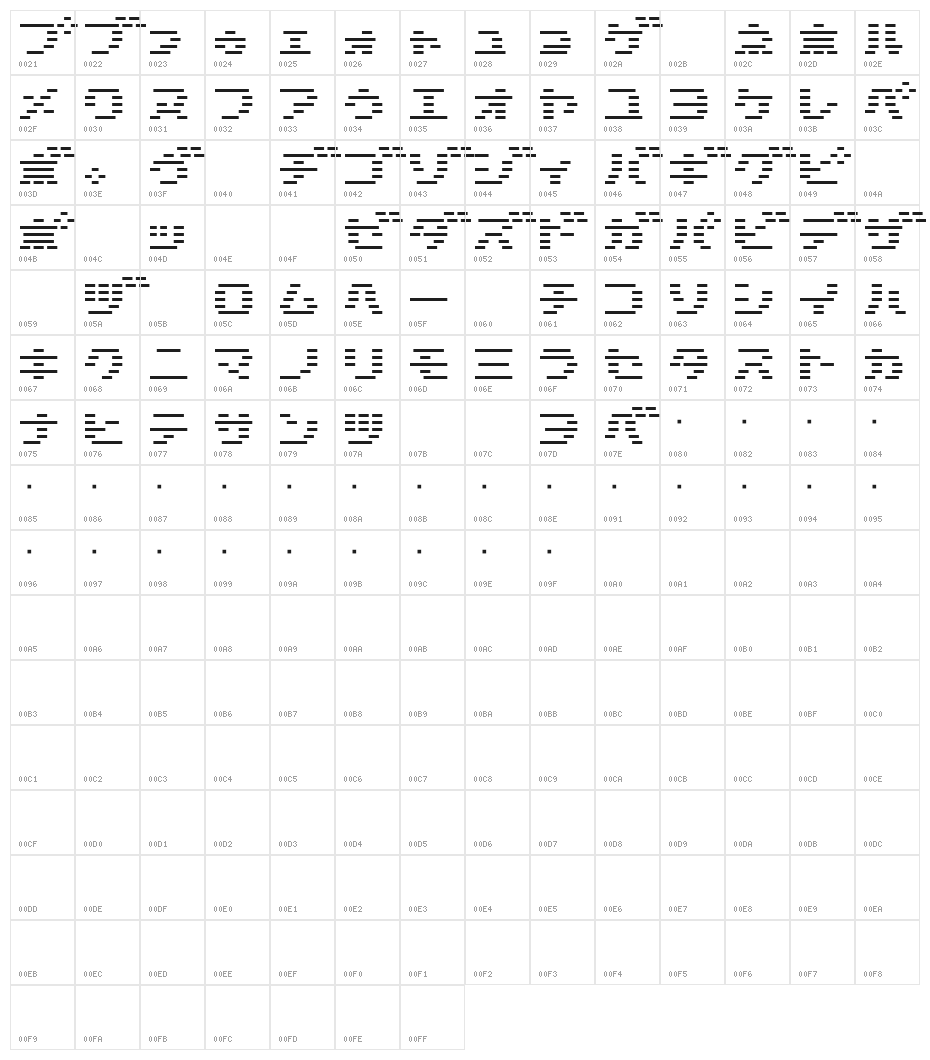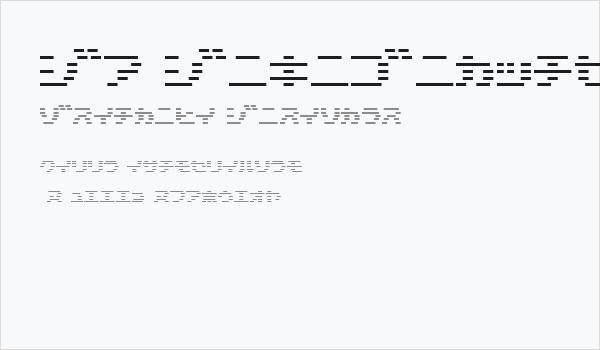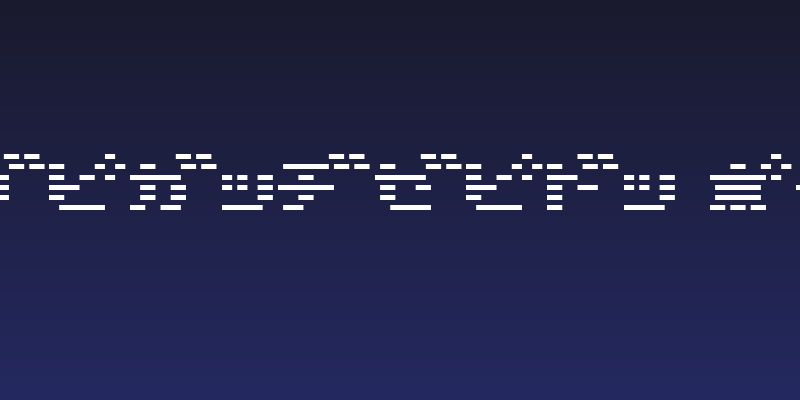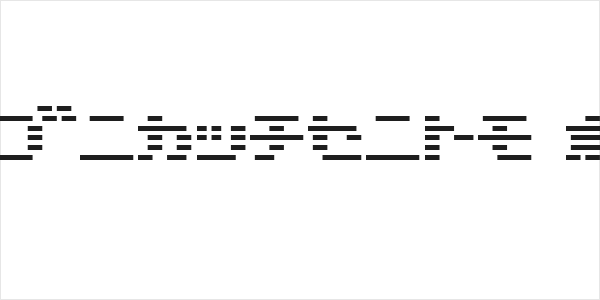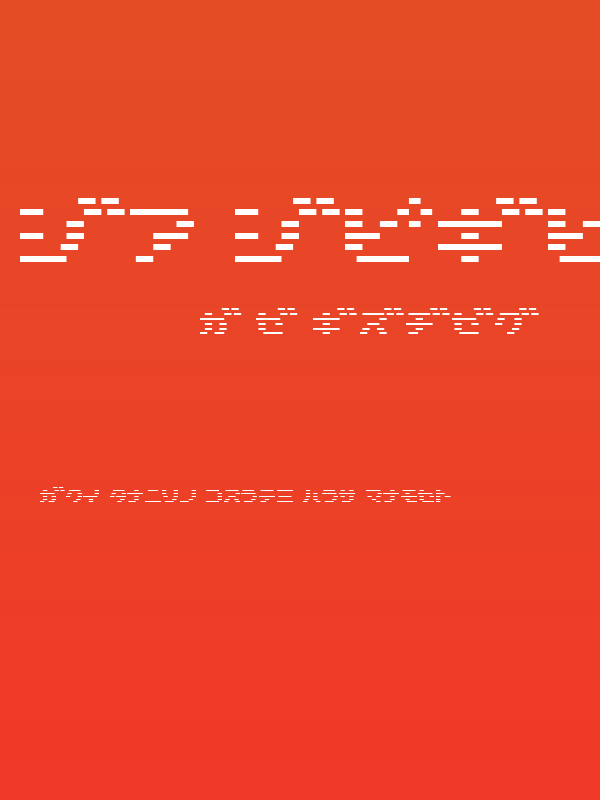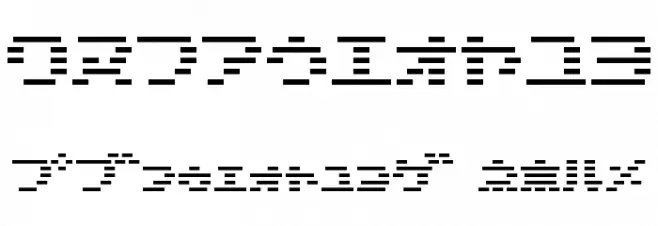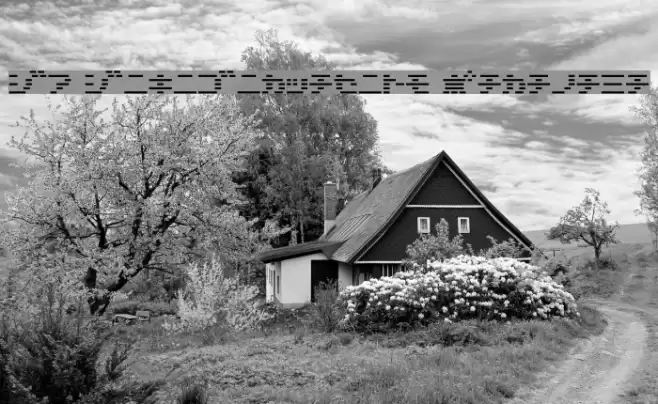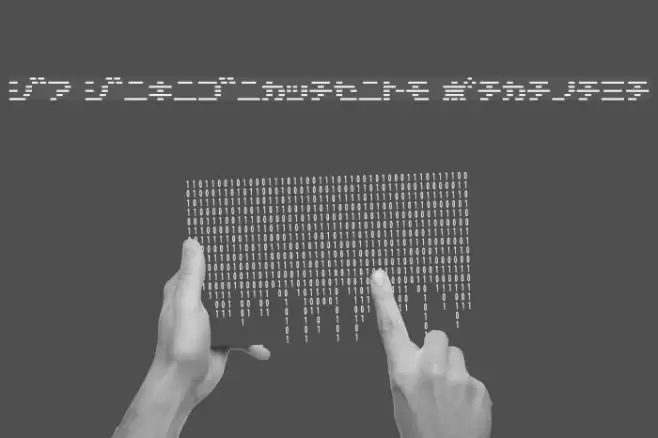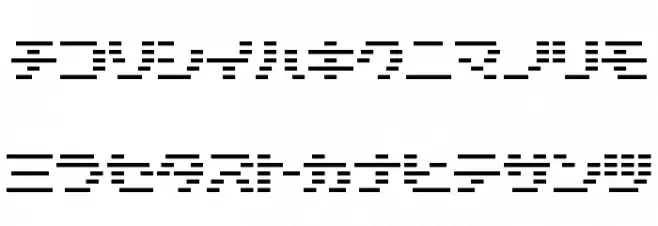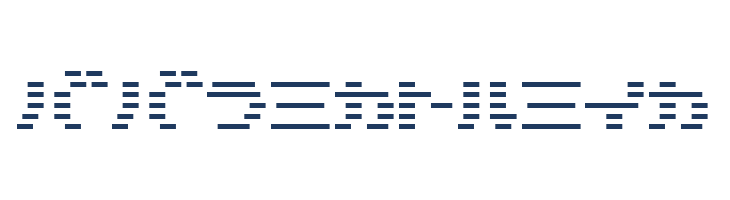
D3 DigiBitMapism Katakana Font
| समग्र शैली | Vintage |
| उपयोग का मामला | Logos, Headlines, Digital Art |
| सुझाए गए प्रोजेक्ट | Ideal for retro-themed designs, video game graphics, digital art projects, and any creative work that seeks to capture a vintage tech aesthetic. |